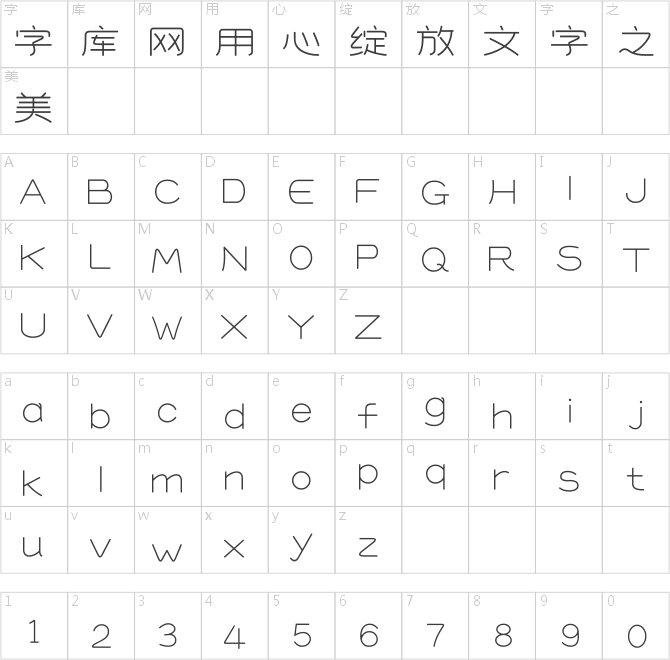
字体名称: 上首秀圆体
上首秀圆体,字体风清新秀丽,笔画瘦长,转角圆润,是此套字库的亮点。字库整体特征柔和、圆润,具有现代感十足,适用于搭配标志、广告标语、商业广告等高端属性。
上首秀圆体字体字库是一款让人赏心悦目、百看不厌的中文字体,适合各类广告和产品包装设计应用,字体大小2.74MB,格式为ttf字体,上传用户是上首造字,作者/版权方为上首造字